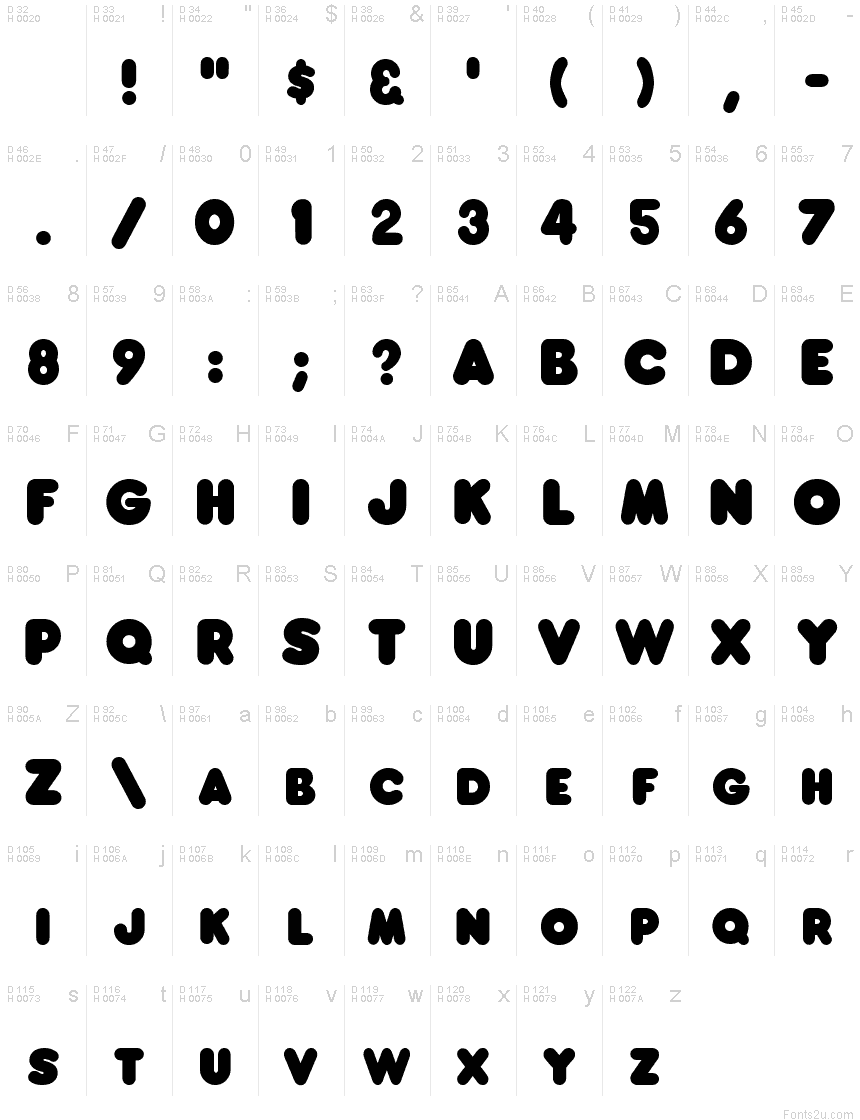
Franks od E. Leacha to darmowy, komiksowy krój pisma typu display z dużymi, miękkimi kształtami, które wyglądają, jakby zostały uformowane z elastycznego winylu. Masywne, zaokrąglone litery są umieszczone blisko siebie, tworząc wyrazisty, przyjazny blok kolorów, który sprawia wrażenie zabawy, ale pozostaje przejrzysty. Dzięki stałemu rytmowi kształtów tekst jest czytelny nawet w dużych rozmiarach i zachowuje swój charakter.
Ten darmowy font Franks świetnie sprawdzi się na okładkach książek dla dzieci, opakowaniach zabawek, zaproszeniach urodzinowych, naklejkach, plakatach na imprezy szkolne i wesołych miniaturkach na YouTube. Doskonale nadaje się również do logotypów marek rodzinnych i tytułów gier, które potrzebują odrobiny uroku. Spróbuj połączyć Franks z prostym, geometrycznym bezszeryfowym krojem w tekście głównym i pozwól Franks przejąć rolę w wyrazistych, dużych nagłówkach.